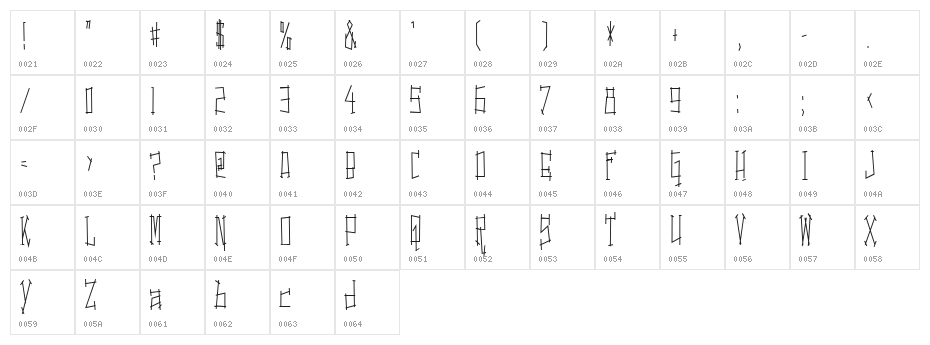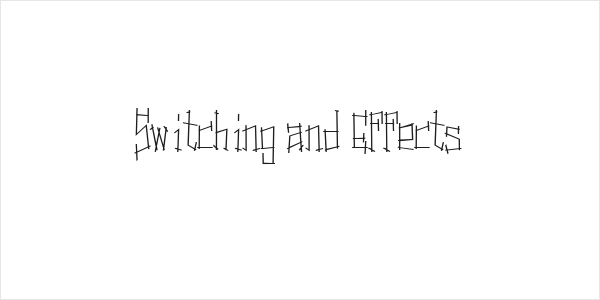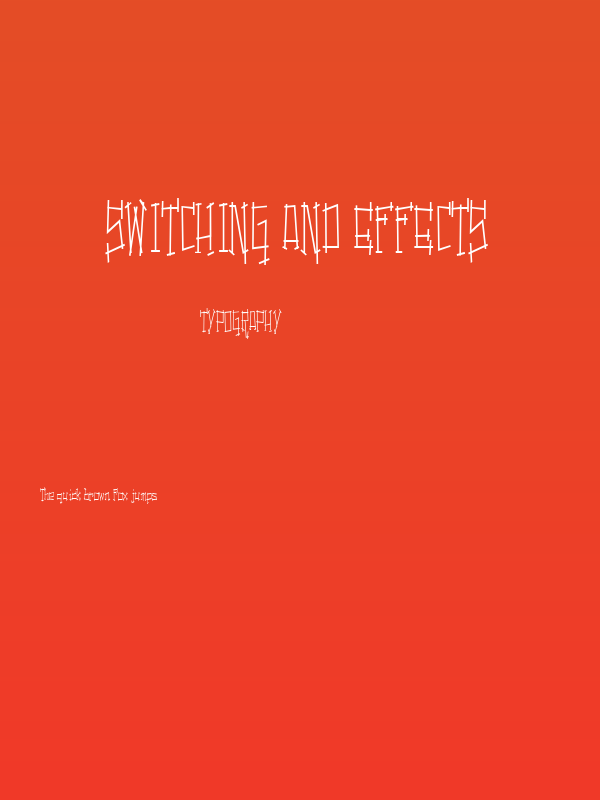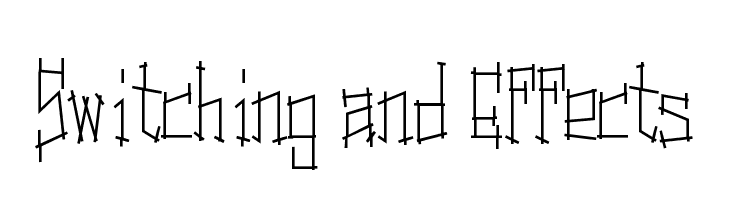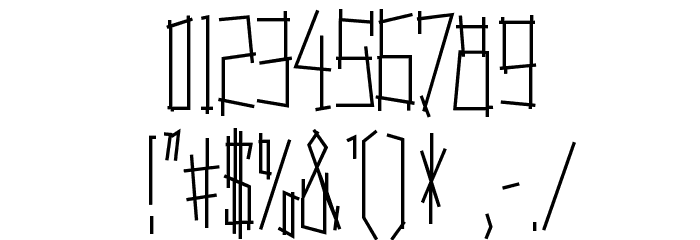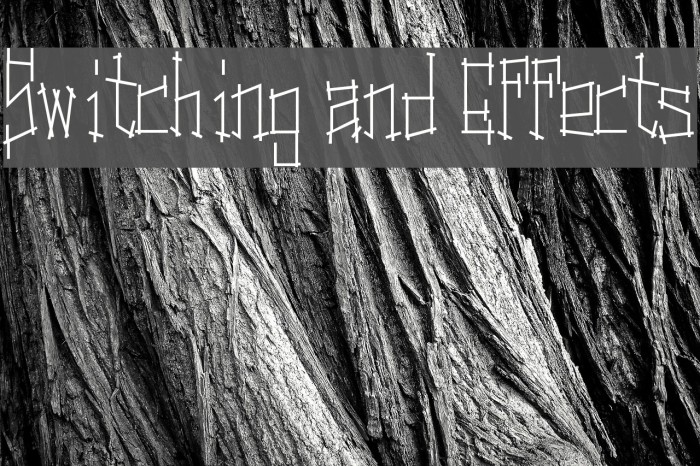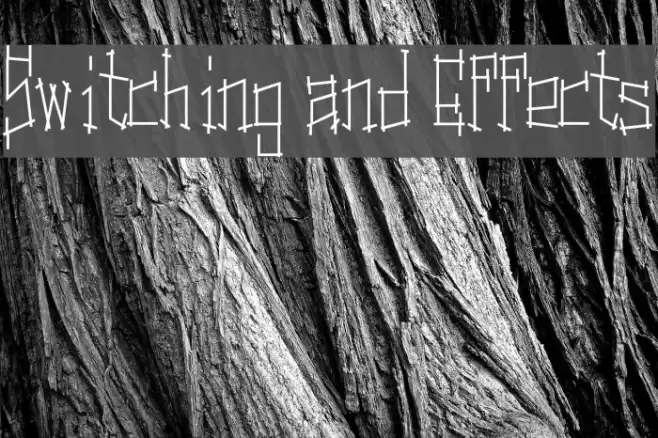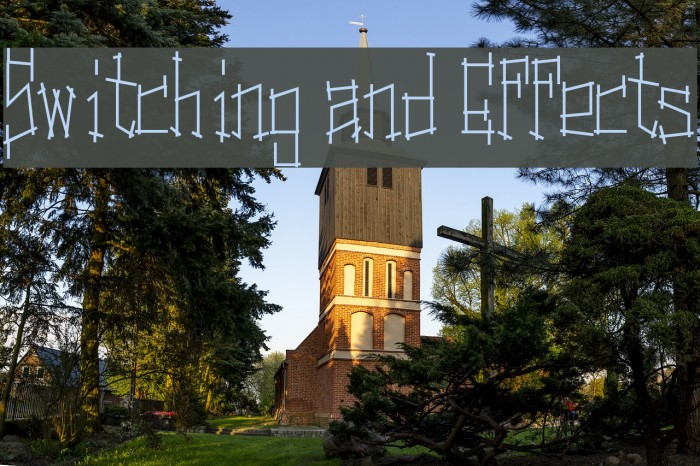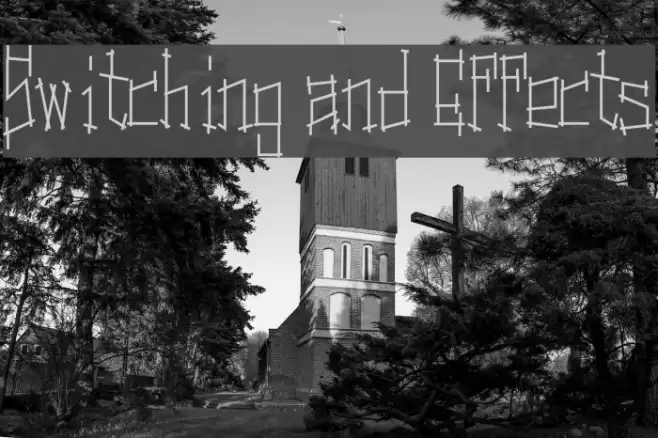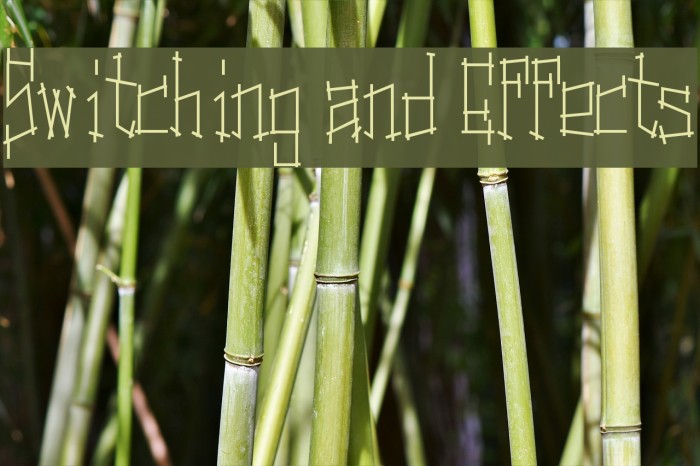
Switching and Effects Font
| चौड़ाई | Condensed |
| उपयोग का मामला | Logos, Posters, Titles |
| सुझाए गए प्रोजेक्ट | Ideal for sci-fi themed projects, digital art, futuristic branding, or any creative work requiring a unique and modern typeface. |